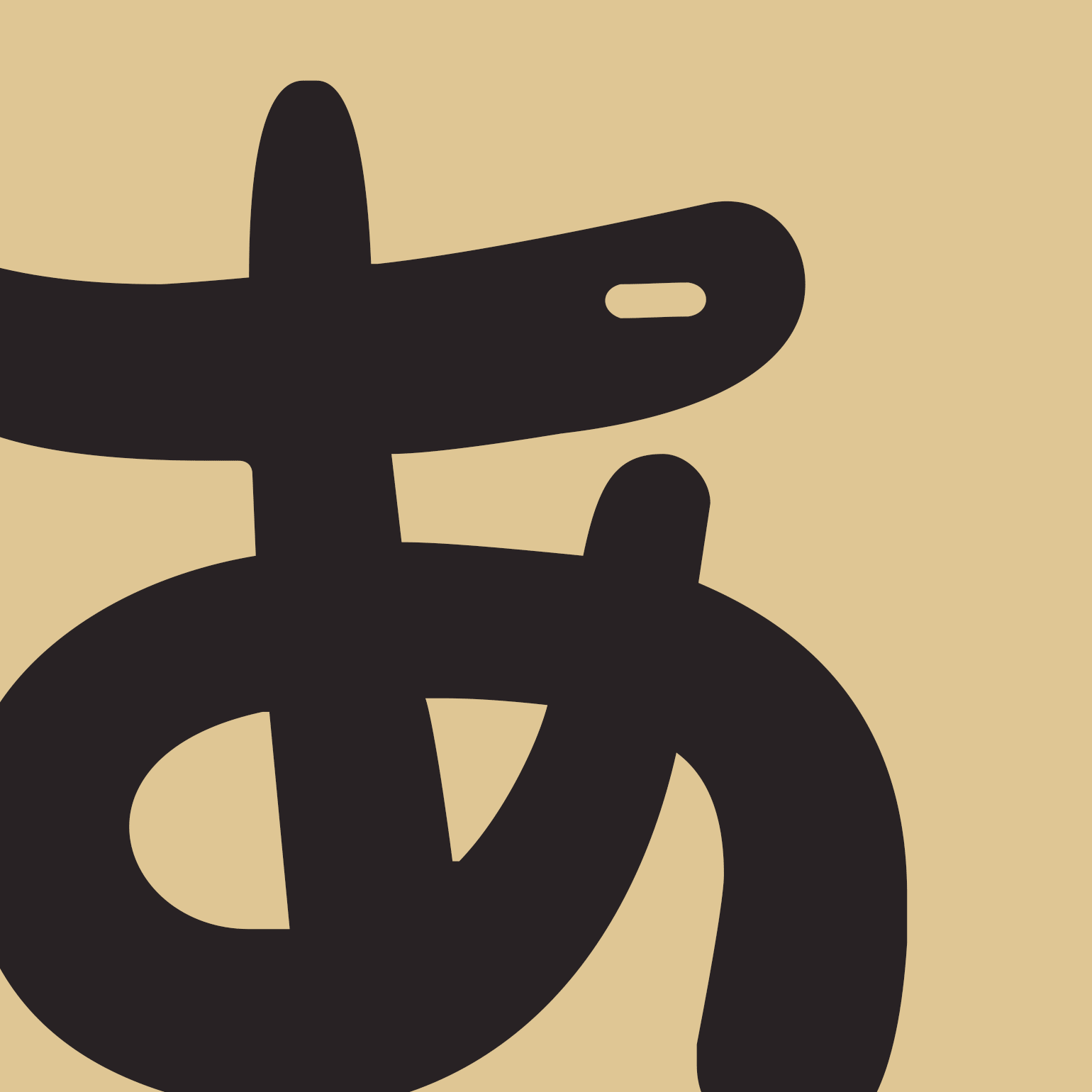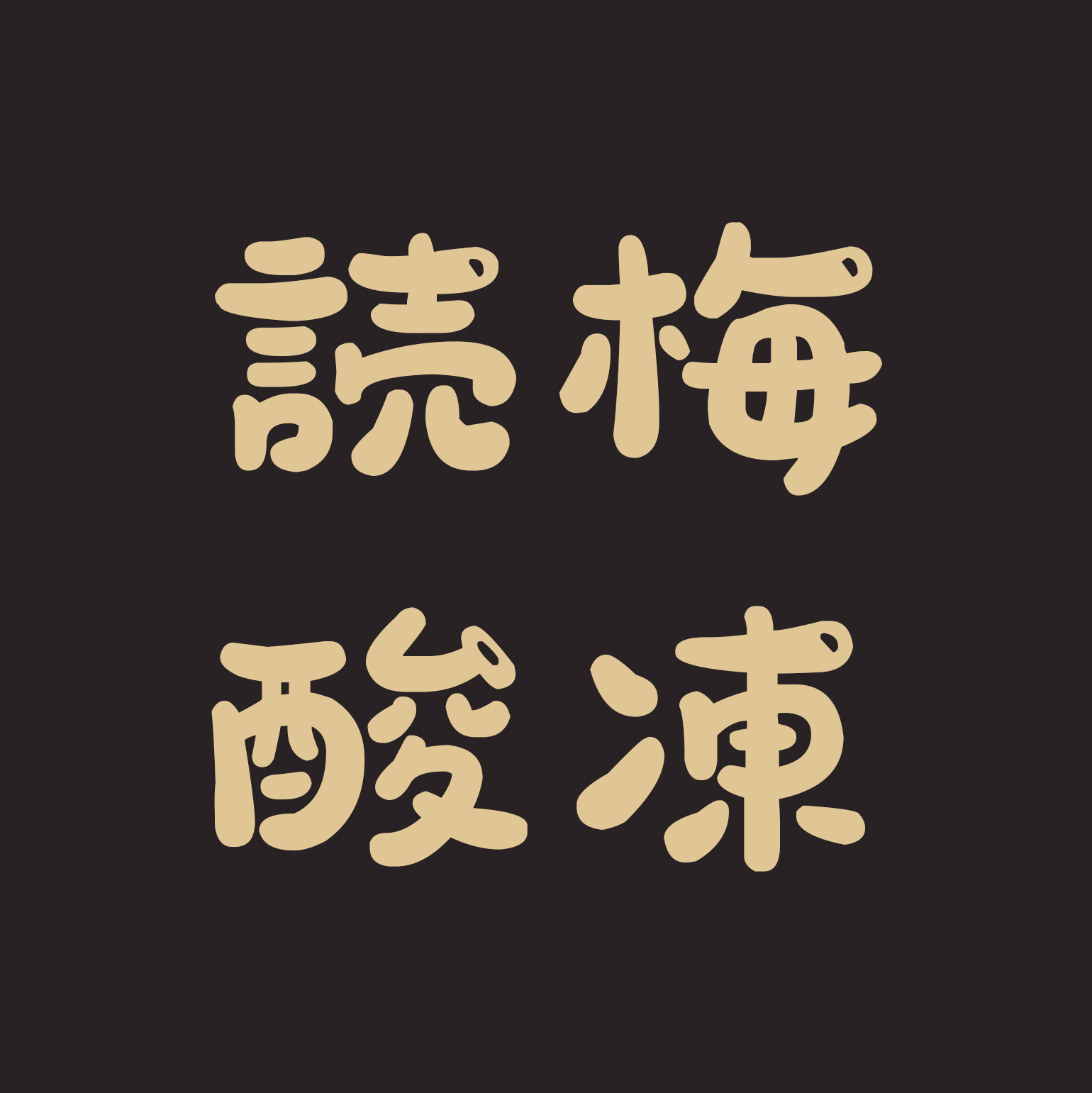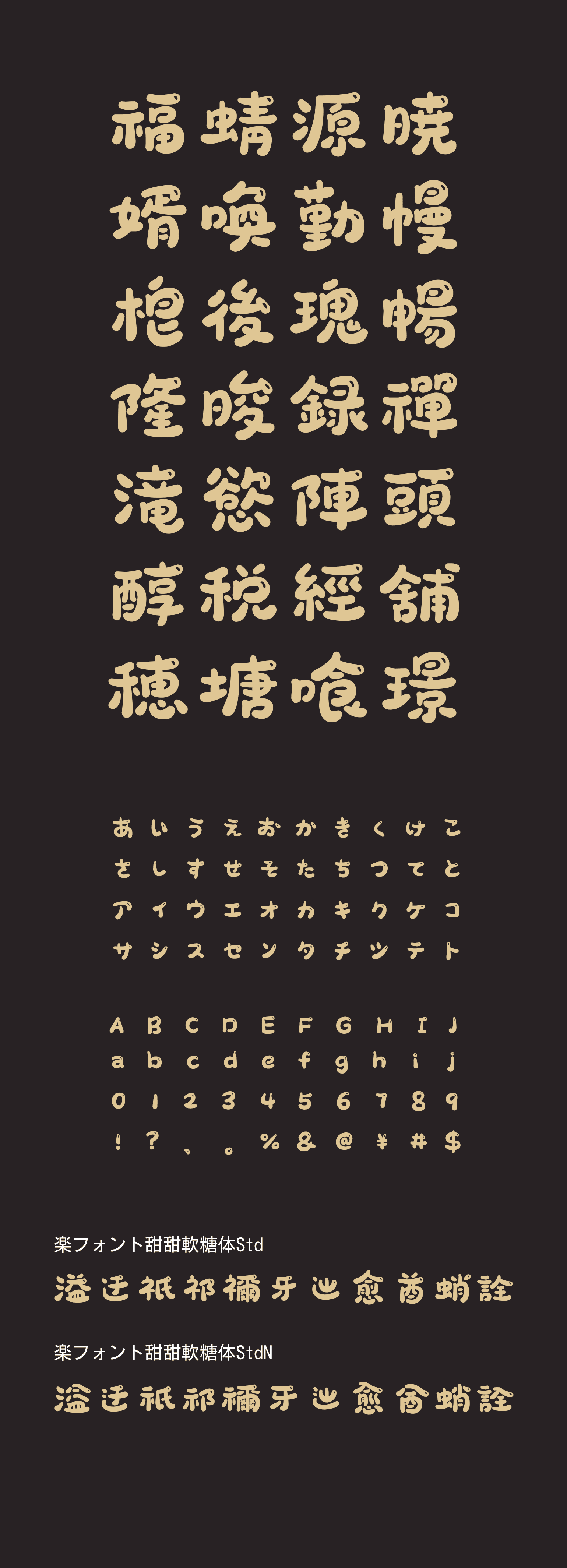
甜甜軟糖体(てんてんなんとうたい)
この書体は、丸みを帯びた柔らかな線と変化に富んだデザインが特徴です。字形は大胆で、遊び心にあふれています。ハイライトのアクセントが文字に軽やかさを加え、全体的により生き生きとした印象を与えます。絵本や児童書、広告、アート作品、看板、チラシなど、幅広い用途で多彩な表現が可能です。